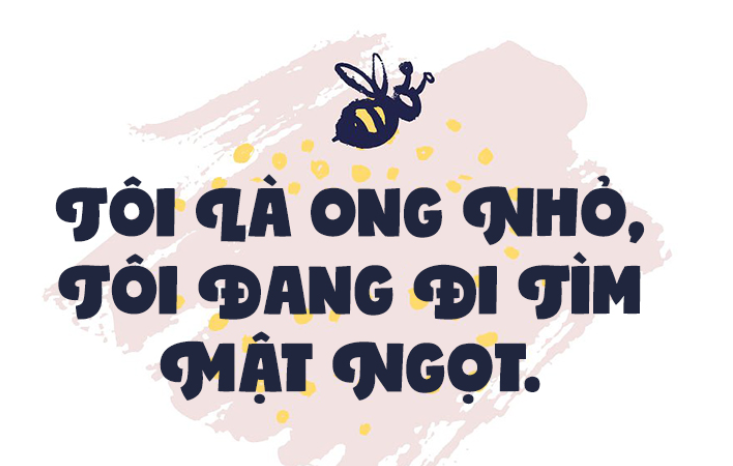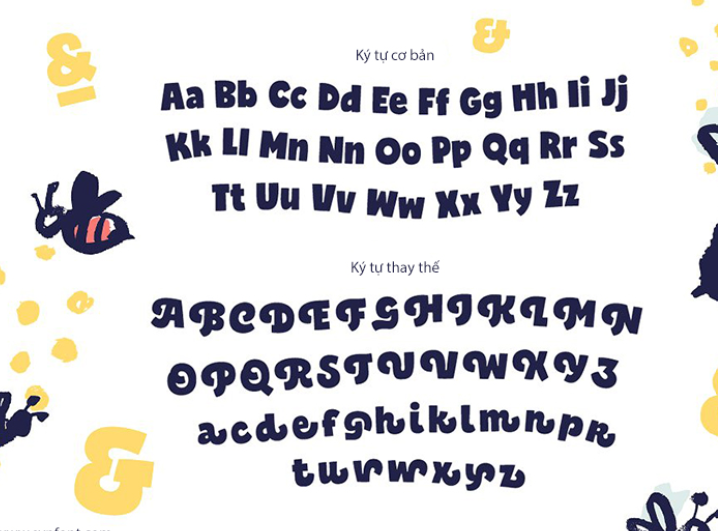
SVN Bjola là bộ phông chữ thuộc dòng Chunky Display mang phong cách vui nhộn, mập mạp và tràn đầy năng lượng tích cực. Được sáng tạo bởi xưởng thiết kế Vatesdesign và được đội ngũ SVN tinh chỉnh hoàn thiện hệ thống dấu tiếng Việt, Bjola là lựa chọn hàng đầu cho các thiết kế logo ngành bánh kẹo, bao bì sản phẩm trẻ em, đồ ăn vặt và nhãn dán đồ uống tươi sáng. Doozypack.vn cung cấp link download font SVN Bjola Việt hóa chuẩn kỹ thuật, giúp bạn sở hữu phông chữ béo đáng yêu mà không lo gặp bất kỳ lỗi hiển thị dấu thanh nào khi thiết kế in ấn.
Đặc điểm thẩm mỹ độc đáo của bộ font SVN Bjola
Bjola không đi theo sự nghiêm nghị của các phông chữ hình học truyền thống; nó chinh phục người xem nhờ cấu trúc chữ đầy đặn, ngộ nghĩnh và mang đậm tinh thần tối giản ấm áp của vùng Bắc Âu.
Phong cách Chunky Display mập mạp và tràn đầy năng lượng
Đặc trưng lớn nhất của SVN Bjola là độ dày nét chữ (weight) cực lớn cùng những mảng màu đặc vững chãi. Cấu trúc chữ gợi liên tưởng đến những chiếc bánh quy nướng vàng ươm hoặc các khối đất nặn tròn xoe trong thế giới thiếu nhi. Nét chữ to bản tạo ra một sức nặng thị giác vượt trội, giúp tiêu đề bản thiết kế của bạn ngay lập tức chiếm trọn ánh nhìn của khách hàng từ khoảng cách xa trên kệ hàng siêu thị.
Cấu trúc chữ bo tròn thân thiện và dễ mến
Tất cả các góc cạnh của font SVN Bjola đều được bo cong mềm mại một cách có chủ đích, loại bỏ hoàn toàn cảm giác sắc nhọn hay nguy hiểm. Phong cách này mang lại sự an tâm, thân thiện và tươi vui, cực kỳ ăn ý với các thương hiệu mẹ và bé, đồ chơi giáo dục hoặc các dòng thực phẩm hữu cơ hướng đến sự lành tính cho cả gia đình.
Ưu điểm nổi bật của bản font SVN Bjola Việt hóa
Khi ứng dụng các phông chữ nét dày vào thị trường trong nước, sự chỉn chu về dấu câu là yếu tố quyết định đến tính chuyên nghiệp của bản thiết kế:
- Khắc phục triệt để lỗi dấu tiếng Việt: Phiên bản tải font SVN Bjola Việt hóa đã được đội ngũ SVN trau chuốt thủ công từng dấu câu. Các dấu sắc, huyền, hỏi, ngã, nặng được vẽ mập mạp, bo tròn đồng điệu với thân chữ gốc, không gây cảm giác chắp vá hay đè nét làm mất tính thẩm mỹ.
- Bảo đảm tính đồng nhất thương hiệu: Việc tải font Việt hóa font SVN Bjola chuẩn giúp bạn tự tin dàn trang tiêu đề tiếng Việt mà không lo hiện tượng lỗi ô vuông hay nhảy về font hệ thống khô khan.
Lời khuyên từ xưởng in: Vì Bjola là phông chữ có nét chữ rất dày và diện tích mảng mực lớn, khi bạn thiết kế in ấn trên chất liệu giấy Kraft hoặc giấy có bề mặt nhám thô, hãy ưu tiên sử dụng định dạng OTF và tăng nhẹ khoảng cách giữa các chữ cái (Tracking) để tránh hiện tượng mực bị lan làm bít các khe chữ nhỏ như chữ ‘e’ hay ‘a’.
04 Ứng dụng thực tế của font SVN Bjola trong sản xuất bao bì
Sự tươi vui và ngọt ngào của Bjola mang lại hiệu ứng thị giác đắt giá trên các dòng sản phẩm bao bì thực tế do Doozypack.vn sản xuất:
- Hộp giấy bánh kẹo & Đồ ăn vặt (Snacks): Nét chữ béo mập gợi cảm giác ngon miệng, rất hợp làm tiêu đề chính trên hộp bánh cookie, túi kẹo dẻo hoặc nhãn dán đồ uống giải khát.
- Bao bì sản phẩm trẻ em & Đồ chơi: Dùng cho tên thương hiệu đồ chơi, bộ xếp hình hoặc hộp quà tặng thôi nôi, tạo sự hào hứng và gần gũi cho các bé.
- Tem nhãn dán Sticker & Decal tròn: Với hình khối chắc chắn, font Bjola cực kỳ phù hợp để in các tem decal tròn hoặc tem niêm phong hộp hàng, giúp sản phẩm trông sinh động hơn.
- Túi giấy thời trang nhí & Thú cưng: Tên cửa hàng in bằng font Bjola trên túi giấy trắng cán màng mờ tạo phong cách trẻ trung, hiện đại và năng động.
03 Lưu ý kỹ thuật khi in ấn với phông chữ nét dày mập Bjola
Việc sản xuất bao bì thực tế sử dụng các phông chữ có đường nét to bản như Bjola đòi hỏi sự am hiểu kỹ thuật chuyên sâu tại xưởng in Doozypack.vn:
- Kiểm soát hiện tượng tràn mực (Dot Gain) tại khe chữ nhỏ: Các khe hở bên trong chữ Bjola thường rất nhỏ. Khi in trên giấy có độ thấm mực cao, mực có thể bị lan làm bít kín các lỗ hở này. Bạn nên giữ size chữ tiêu đề tối thiểu từ 10pt trở lên để đảm bảo độ sắc nét.
- Lựa chọn hệ màu rực rỡ: Phong cách Bjola đẹp nhất khi phối với các tông màu tươi sáng hoặc màu Pastel. Một đường viền (Stroke) mỏng quanh chữ cũng giúp tiêu đề trông “nổi” và sắc nét hơn trên vỏ hộp.